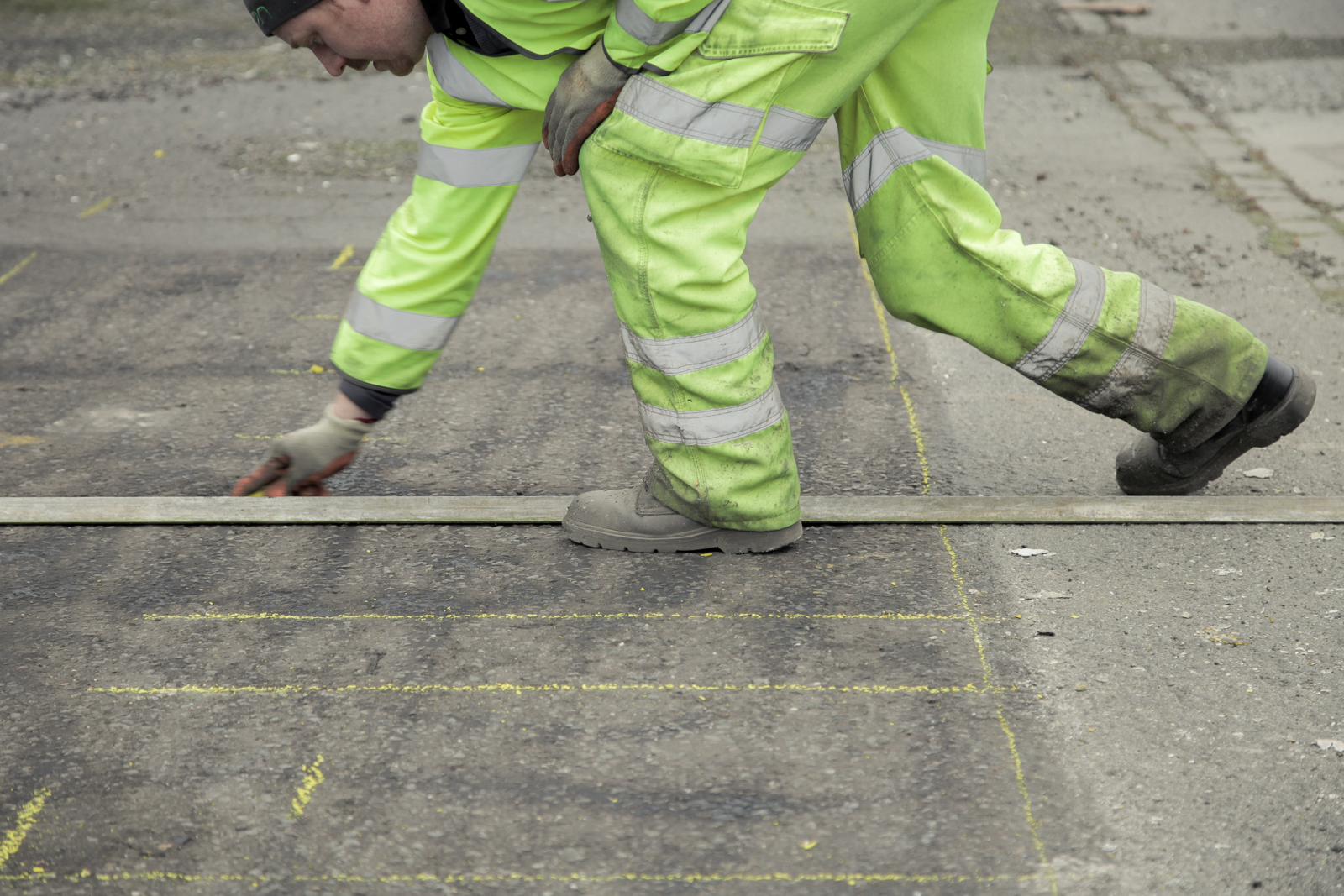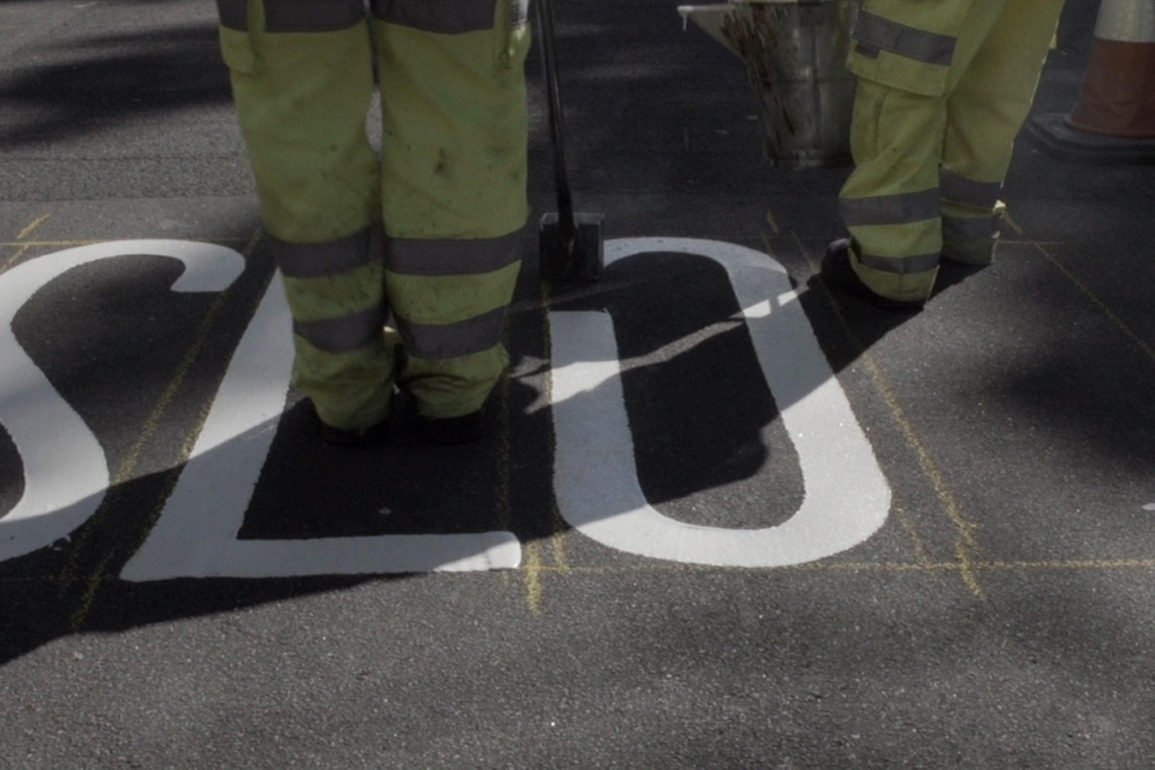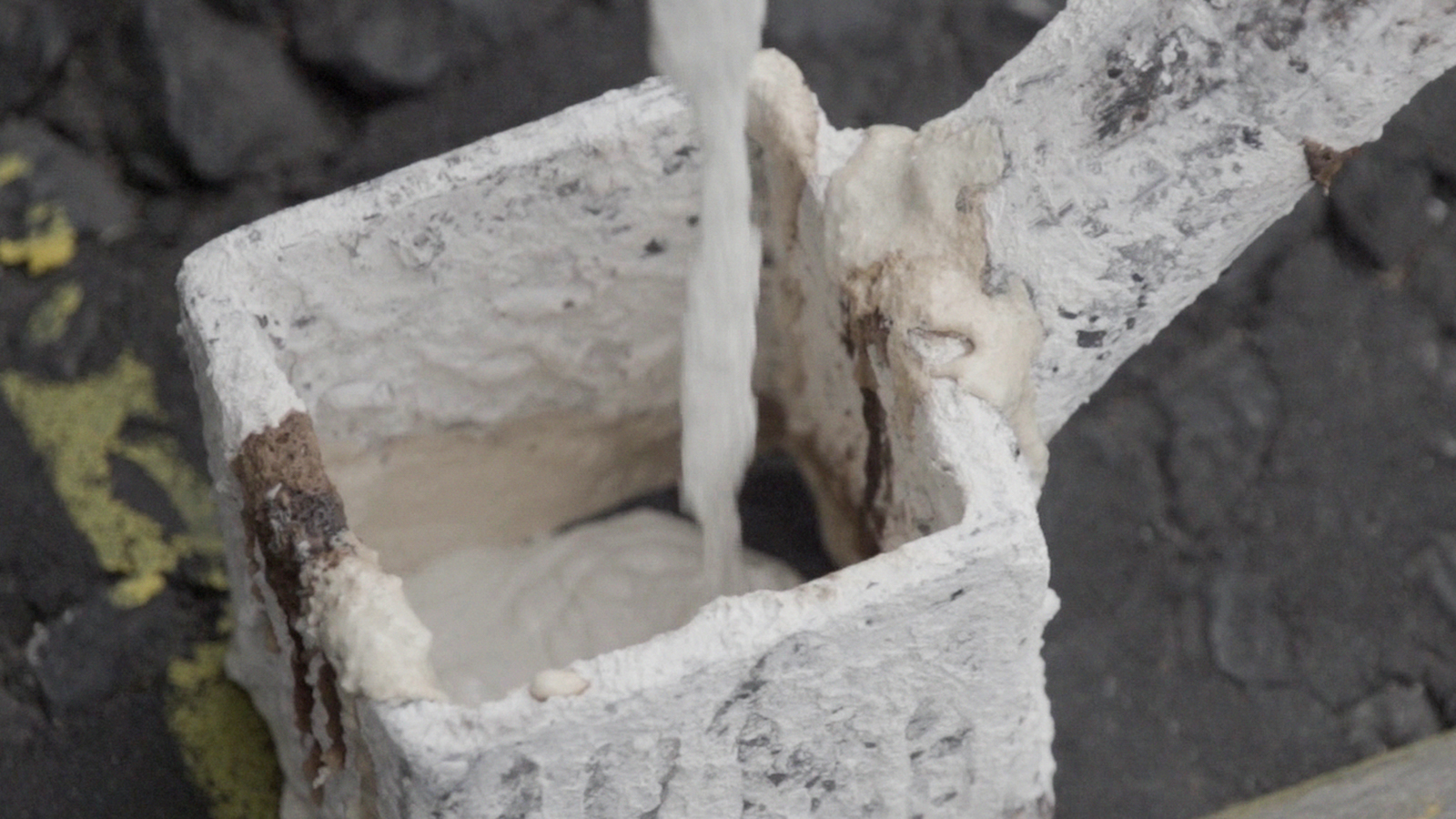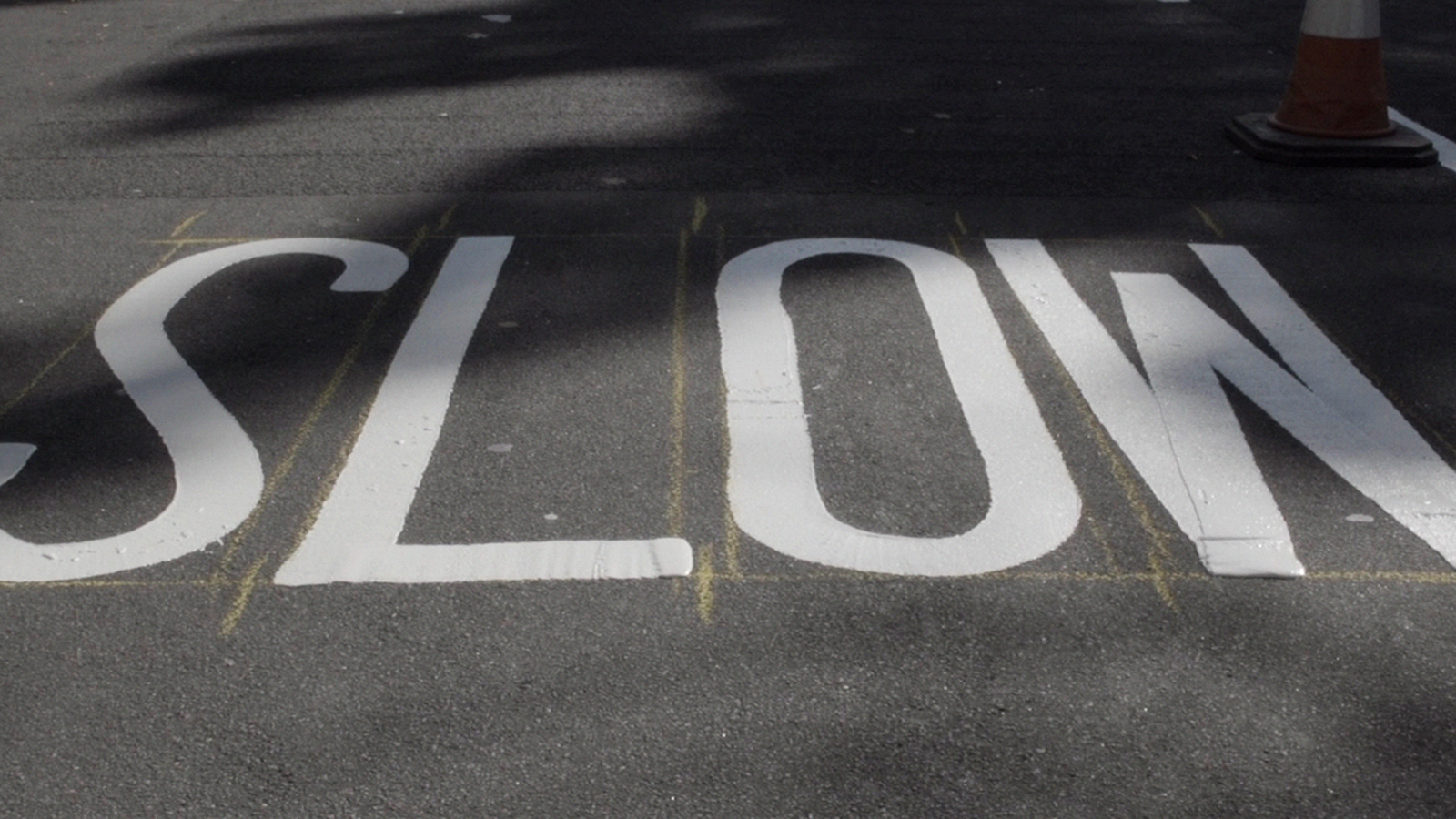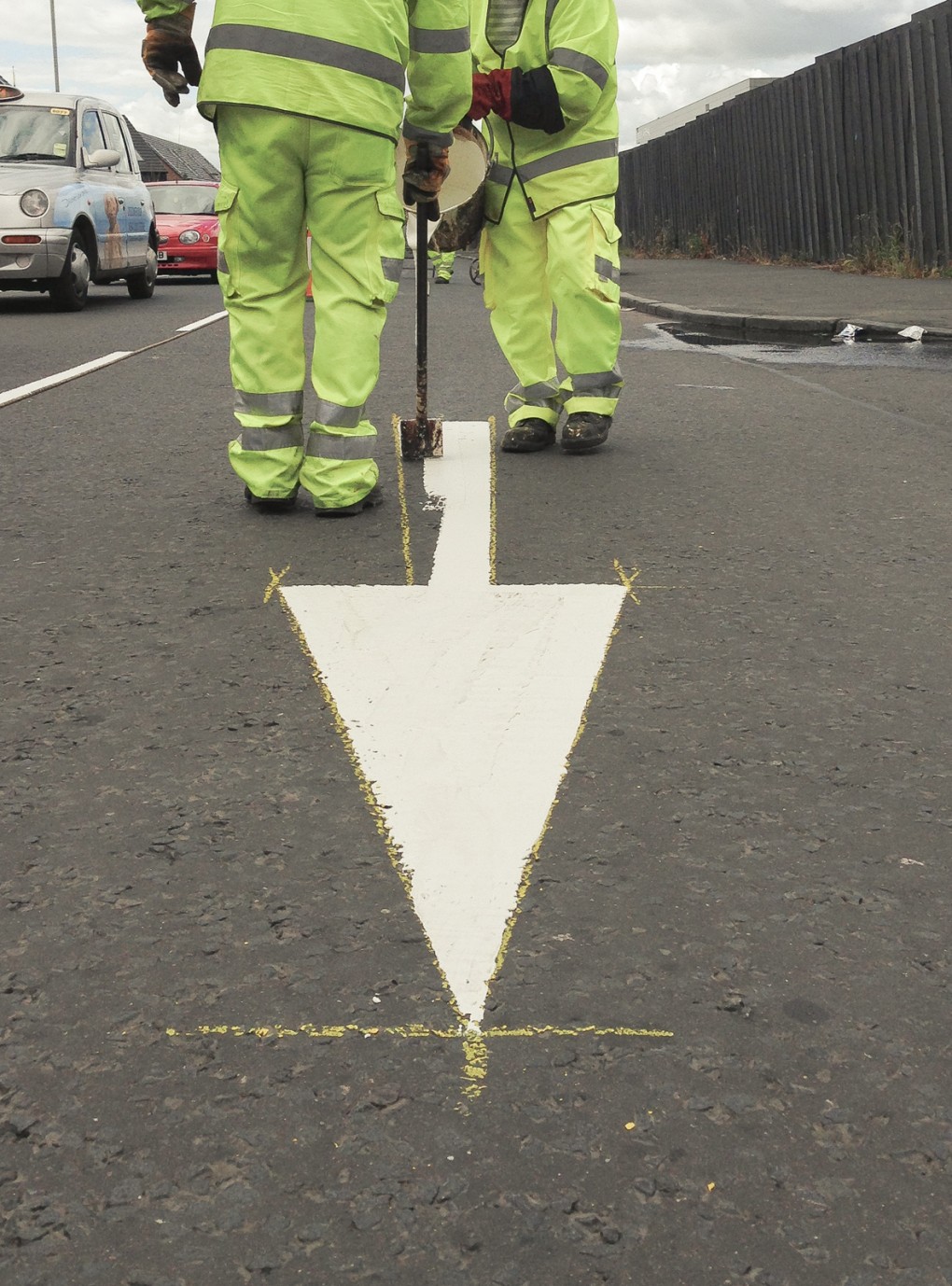
Le calpestiamo ogni giorno, senza farci troppo caso. Ci passiamo sopra con le ruote della bicicletta, dello scooter, dell’automobile e dell’autobus. Ci accorgiamo quando le rifanno — linde e brillanti come le foglie cadute da un albero e illuminate dal sole dopo un temporale. Le memorizziamo sui manuali di scuola guida — segnaletica orizzontale — e talvolta notiamo la loro bellezza astratta, ma c’è qualcuno che quelle linee e quelle lettere le disegna, e serve un’abilità che forse meriterebbe un po’ più di attenzione.
«Non è solo un lavoro — è una danza», dice a un certo punto dei protagonisti di Roadliners, breve documentario prodotto nel 2016 dallo studio creativo scozzese O Street. E sembra proprio di vederlo danzare l’operaio addetto a tracciare sull’asfalto le linee, muovendosi sapientemente tra gli spazi vuoti delle lettere per non calpestarli.
«Vedere un maestro roadliner al lavoro fa venire in mente un calligrafo giapponese o un apprendista pittore del Rinascimento», dicono i registi del corto, che mentre se ne andavano in giro per le strade cercando ispirazione, hanno scoperto per caso il fascino di questi anonimi “calligrafi” con le divise fluorescenti, decidendo quindi di celebrarli attraverso un video.
Commentato in uno scozzese stretto e perlopiù incomprensibile, il filmato riesce ad ammaliare anche solo con le immagini: la vernice calda che cola, i movimenti fluidi e decisi, le linee diritte e quelle curve, le lettere che appaiono sul manto della strada.